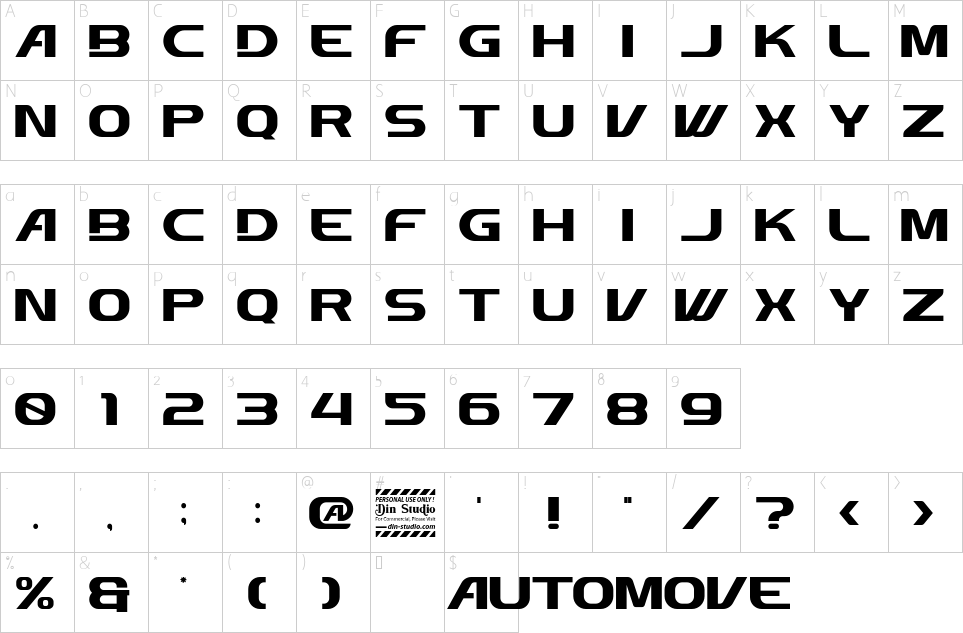
A Automove font é uma elegante e sofisticada escolha para qualquer designer gráfico buscando uma fonte minimalista e moderna. Lançada por Donis Miftahudin, esta fonte de texto foi projetada para oferecer uma estética harmônica que se adapta bem a um amplo range de aplicações. Seu design limpo e fácil de ler faz dela uma excelente opção para manuais de instruções, publicações de notícias, design de materiais de marketing, e muito mais. Com seus 614 downloads, é claro que muitos designers encontraram a Automove font valiosa para sua paleta de ferramentas. Engajante e versátil, a Automove font é uma excelente escolha para quem procura uma fonte moderna e funcional.